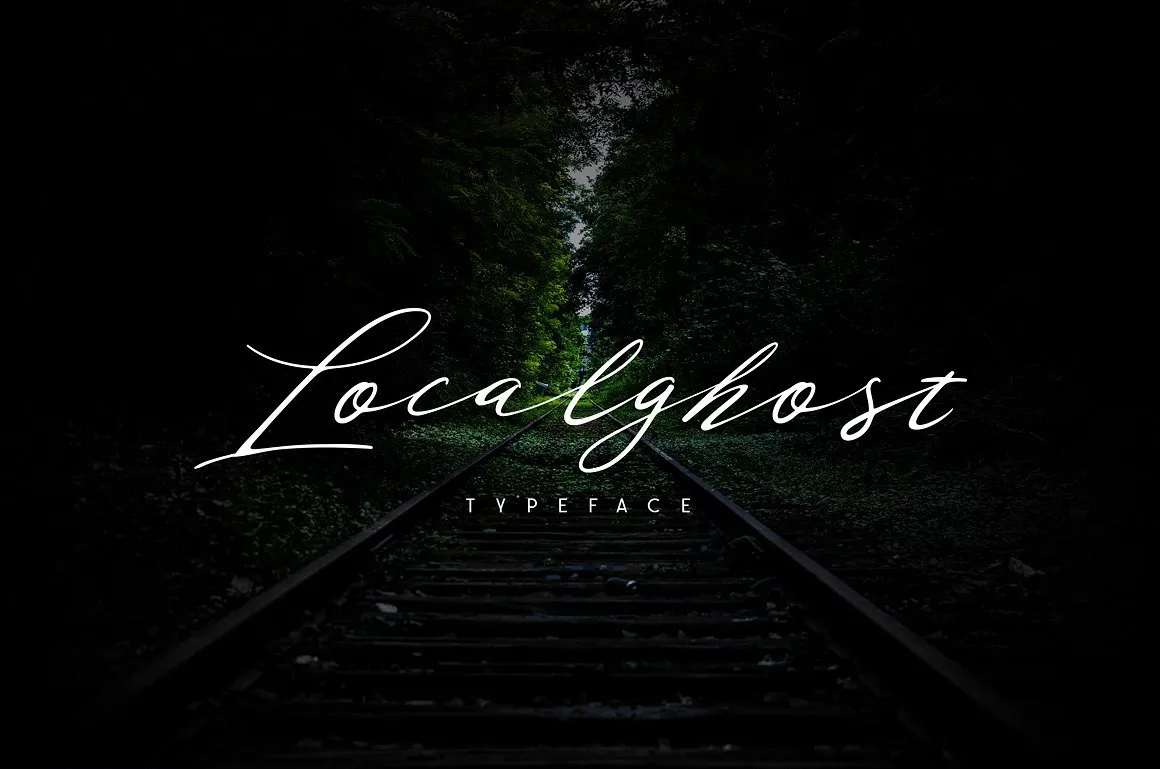
Aqui está uma descrição para a página de download da fonte ‘Localghost Script Font’, escrita de forma envolvente e natural: Estamos muito felizes por você estar olhando ao Localghost Typeface! Esta fonte é perfeita para qualquer projeto gráfico, sempre disponível e pronto para ser integrada com todas as suas necessidades. Você pode conferir no quadro de apresentação acima como ela funciona em diferentes contextos! Desenvolvida pela alit design, a Localghost foi criada usando um estilo de letra script que caracteriza o seu design único. O resultado é uma fonte incrível para dar um toque diferenciado em todos os seus projetos gráficos – seja marca de água, citações, logotipos, designs de painel, criação pessoal, escrita, fotografia, cabeçalhos de blog, cartões de aniversário, convites ou material de estação. Estamos certos de que você vai amar a variedade e o poder da Localghost em qualquer projeto onde seu design precisa ser único e impecável. Instale-a agora e transforme seus projetos!